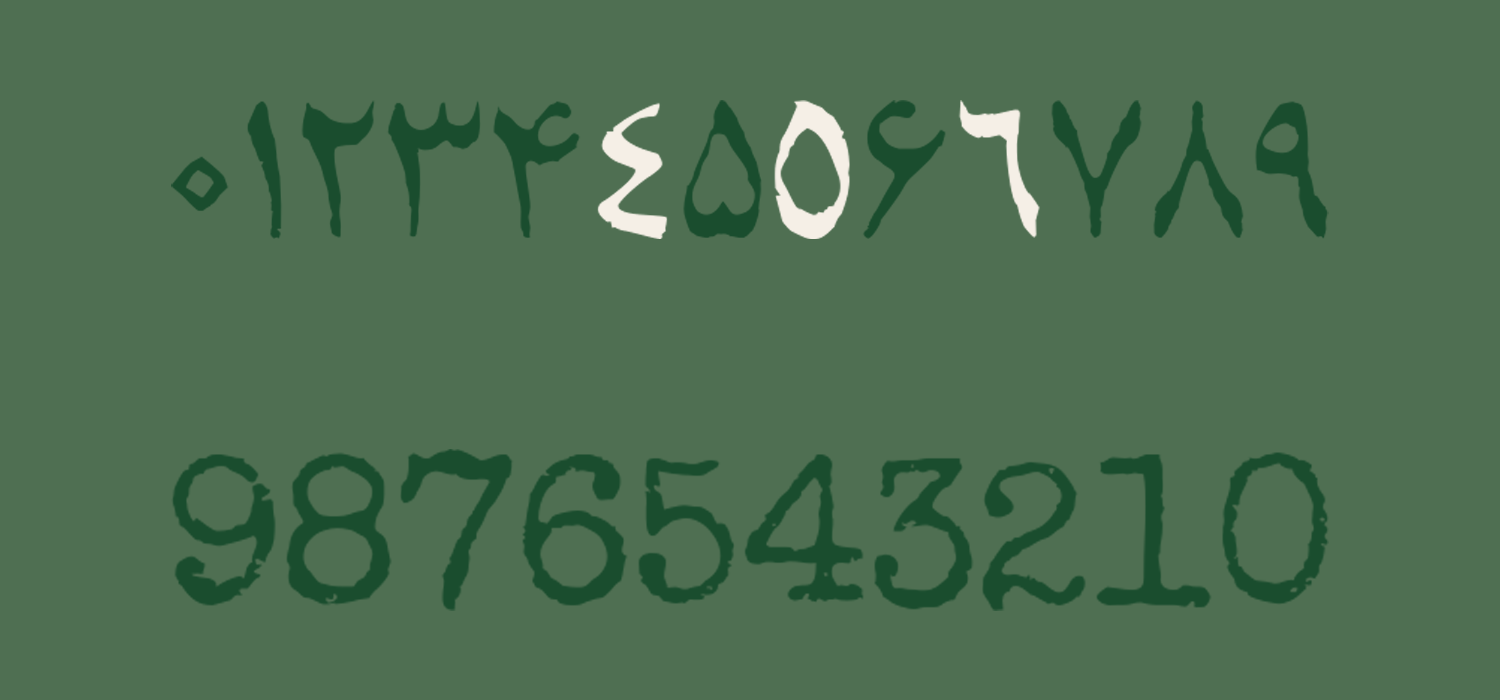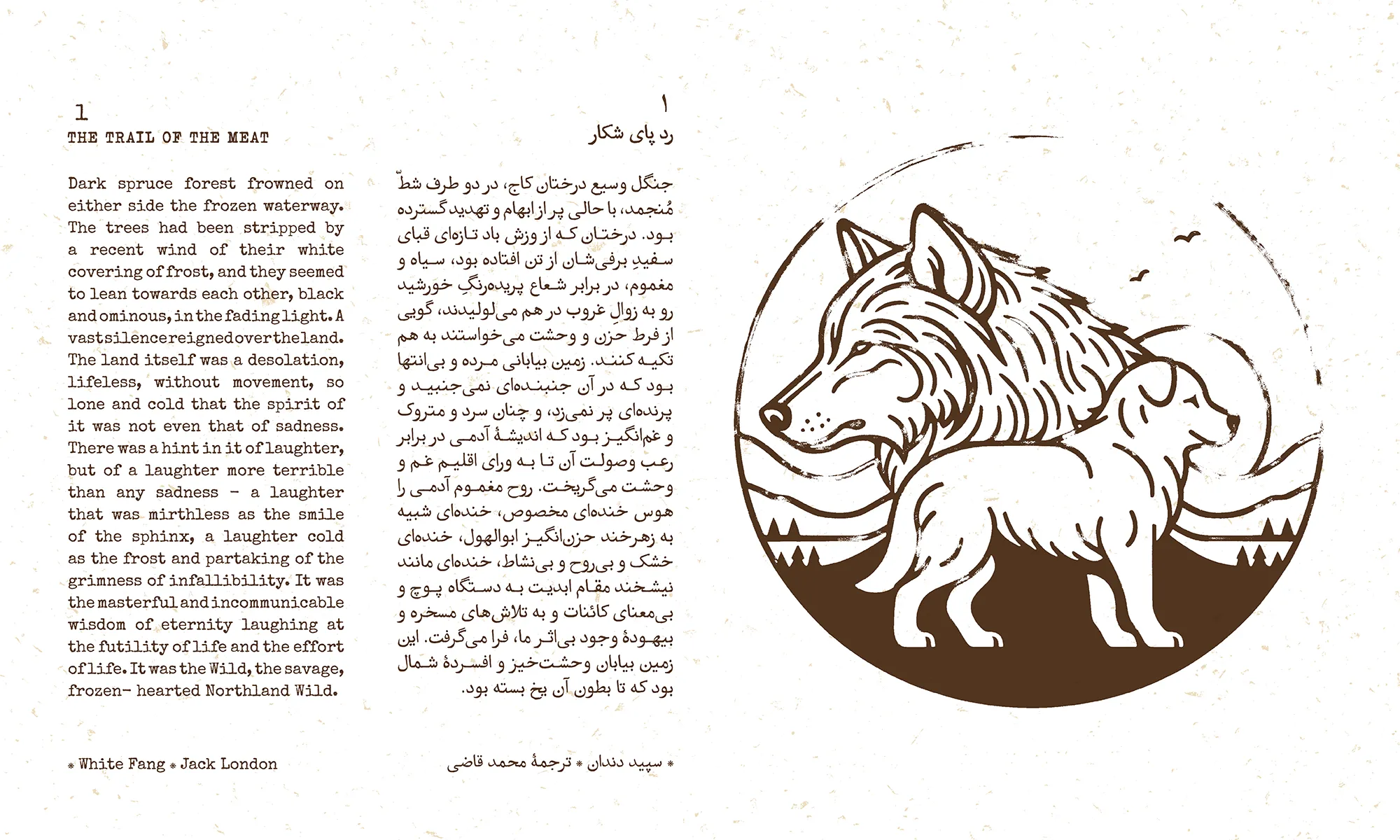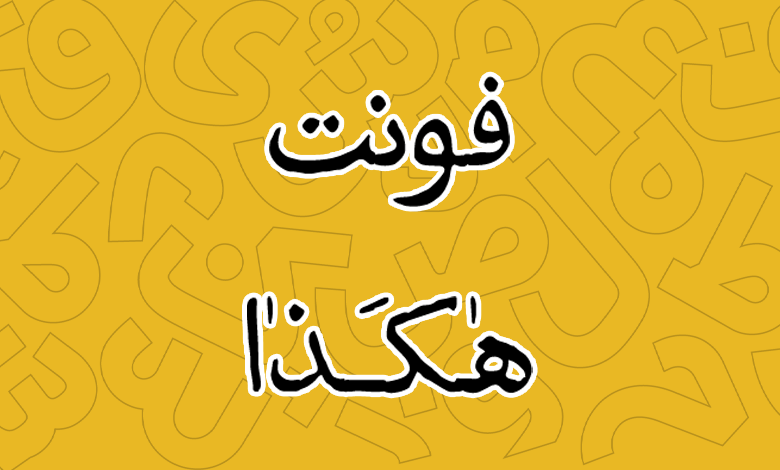
فونت هاکذا (Hakaza)
فونت هاکذا (به انگلیسی: Hakaza) قلمی است که یادآور رایحه مرکب، ماشینهای چاپ و برگرفته از قلب صنعت نشر ایران است که دهه ۵۰ را در ذهن همه تداعی میکند. این فونت دارای ساختاری نوستالژی بوده و با توجه به سبکی که در طراحی حروف دارد، میتوانید استفادههای مختلفی در تبلیغات، عناوین و بهطور کلی محیطهای مرتبط با چاپ باشد.
طراحی این فونت فارسی توسط حسن کریمزاده صورت گرفته و توسعه آن را به قلم نرمافزاری نیز حسین کریمزاده به سرانجام رسانیده است که در نسخه اولیه آن شاهد یک وزن برای این قلم هستیم و احتمالا میتوان انتظار ارائه وزنهای بیشتری از این قلم در آینده بود.
در ادامه این نوشته از سایت فونتچی به نقد و بررسی فونت هاکذا خواهیم پرداخت؛ قلمی که میتوانید برای استفاده در صنعت چاپ، خصوصا کتابهایی با موضوعات رمان، داستانی، تاریخی و قدیمی مناسب باشد که علاوه بر یادآوری دهه ۵۰، رنگ و بوی صنعت چاپ را در ذهن خواننده بیشتر تداعی خواهد کرد.
فونت هاکذا قلمی خاطرهانگیز با رایحهای از مرکب چاپ است که با خود توشهای با پیشینه دیرینه از صنعت نشر ایران امروزی را داشته و از دل سطربهسطر نشریات دههی پنجاه ایران متولد شده است.
با اینکه قلم هاکذا را میتوان در دسته تایپفیس طبقهبندی کرد؛ اما به معنی بازسازی عینبهعین نبوده و اصلاحات ریز و درشت متعددی در جزئیات تمامی حروف و گلیفها ایجاد شده تا خوانش این قلم برای خواننده لذتبخشتر از زمانهی خود شود.
سبک طراحی و وزن فونت هاکذا
در طراحی فونت هاکذا از طراحی نسخ بهره برده شده است که با توجه به الگوبرداری از صنعت چاپ ایران در دهه ۵۰، اصلاحات بسیاری در فضاهای مثبتومنفی قلم اعمال شده است. کرسی منظم حروف و نقطهها تغییرات زیادی بهخود گرفته تا ضمن خاطرهانگیز بودن، برای خوانندگان ارمغانآور همان دهه باشد.
در طراحی این فونت، از فاصلهگذاری مهندسیشده متناسب با حروف و کلمات، و فیزیک کلی قلم بهره برده شده که در متنهایی با سایزهای کوچک، حتی روی کاغذهای بالکی، خوانایی خود را حفظ میکند.
پشتیبانی از ۳ زبان فارسی، عربی و انگلیسی
فونت هاکذا فارسی است و از دل این زبان رشد کرده است. اما با اینحال به لطف رسمخط یکسان از زبان عربی نیز پشتیبانی میکند. پشتیبانی این قلم از زبان عربی بهشکلی است که علاوه بر گلیفهای مشترک فارسی، گلیفهای خاص زبان عربی نظیر «ک، ی، ه، ؤ، ئ» را در خود دارد که در متون خود ساختاری استاندارد بر پایه این زبان داشته باشید.
همنشینی اعراب بر روی حروف بهشکل استانداردی رعایت شده است. در برخی ترکیبات که اعراب دوتایی بهکار رفته باشد ممکن است با چینش اشتباه مواجه شوید که در زیر نیز نمونهای از آن را برای «تشدید و ضمه» مشاهده میکنید که صد البته در نسخههای آتی برطرف خواهند شد.
کلمات فارسی فونت هاکذا یا همنشینی دوستانهای که با حروف انگلیسی دارد، در کنار یکدیگر ساختاری یکپارچه به متن شما خواهند داد که خواننده از خواندن متون لذت میبرد. این فونت همان سبک طراحی چاپی ماشین آلات را برای این زبان دارد.
پشتیبانی از اعداد استاندارد فارسی و عربی
ویژگی دیگر فونت هاکذا پشتیبانی از اعداد استاندارد است که مطابق با زبان صفحه کلید تایپ خواهند شد. اگر صفحه کلیدتان فارسی باشد کلیه اعداد بهشکل فارسی تایپ خواهند شد. در مقابل برای زبان عربی نیز گلیفهای خاص این زبان تایپ خواهد شد که اعدادی همچون «۴۵۶» که متفاوت از «۴۵۶» فارسی هستند بهدرستی تایپ شوند.
همچنین همان سبک فونت که بر مبنای صنعت چاپ دوره معاصر ایران بوده، برای اعداد انگلیسی در نظر گرفته شده است که برای هر سه زبان، در تصویر بالا آنها را مشاهده میکنید.
مناسب برای تبلیغات و صنعت چاپ
فونت هاکذا برای استفاده در محیطهای چاپی بسیار عالی است. از نمونههای دیگر قلمهای مناسب برای این حوزه میتوان به فونت دفتر و فونت گرامافون اشاره کرد که همین سبک و سیاق را در خود دارند.
از این فونت میتوانید برای فونت عنوان در قالب پاراگراف، ستونهای روزنامهای و نیز در قالب عنوان و تیتر برای عنوان کتاب و مجله استفاده است.
یکی از کاربردهای گسترده این قلم در حوزه تبلیغات است که با توجه به سبک نوستالژی و قدیمی این فونت، میتواند بیانگر اصالت باشد. از این قلم میتوانید برای تبلیغات برندهایی که بیش از چند دهه در حال فعالیت هستند استفاده کرد. تفاوتی هم ندارد که جنبه تبلیغاتی برای معرفی محصول یا برند داشته باشد یا اینکه بخواهید در بستهبندی یا طراحی کاور از آن استفاده کنید.
با این همه بیشترین کاربرد این قلم در همان حوزه چاپ است. برای چاپ کتابهای تاریخی، داستانی و رمان میتواند عملکرد عالی داشته باشد که در مقالهای با عنوان بهترین فونت مناسب کتاب، ضمن بررسی ویژگیها به معرفی چندین قلم در این زمینه پرداختهایم.